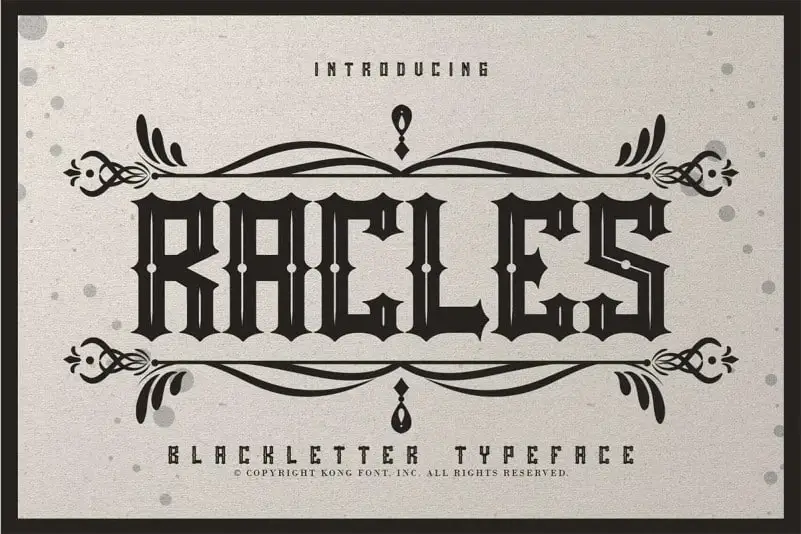
Rackles Blackletter Font – Download Grátis
Olá amantes do design! Estamos com muito prazer apresentando à vocês a Rackles Blackletter Font, uma deliciosa tipografia blackletter altamente autêntica e ousada. Este tipo de texto foi criado pela fontkong e compartilhado no site 99designs. Adicione este estilo-fonte às suas melhores ideias criativas para ver o quão poderoso ele pode ser! A Rackles Blackletter é perfeita para arte calligráfica, desenhos de tatuagem ou até mesmo imitando manuscritos antigos. Eis um exemplo: Imagine criar uma marca memorável que combine a elegância do estilo blackletter com o moderno e vibrante design das chamadas fontes arredondadas. A Rackles Blackletter pode ser o elemento chave para tornar seu trabalho de arte mais original, impactante e único. Não perca tempo! Vá já adquirir sua própria versão desta fonte inovadora. Seja qual for o projeto que você planejar, a Rackles Blackletter está aqui para fazer sua ideia se destacar ainda mais.